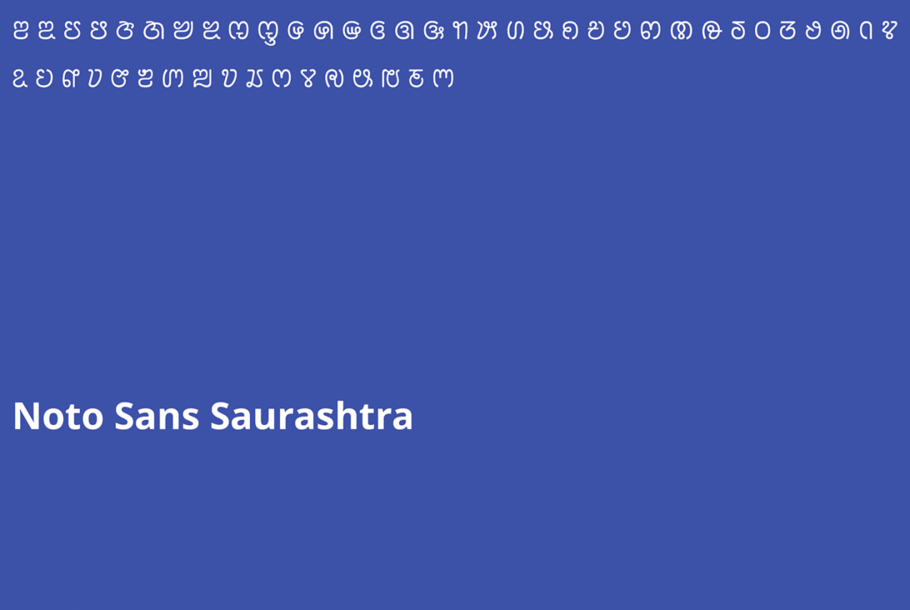
Noto, créée pour Google et ses plus de 800 langages
Une police - cinq ans de production : la police de caractères Noto créée spécialement pour Google couvre plus de 100 systèmes d’écriture, 800 langues et des centaines de milliers de caractères. Fruit d’une collaboration entre Google et Monotype, Noto permet enfin une forme de communication transparente pour des milliards de personnes souhaitant accéder à des contenus numériques du monde entier.
Le brief : « Fini le tofu ! »
Google a donné à Monotype une mission très claire : « Fini le tofu ! ». «Tofu», c’est le surnom que l’on donne aux carrés vides qui s’affichent à la place des caractères lorsqu’un ordinateur ou un site Web ne prend pas en charge la police concernée. Pour répondre à l’exigence de Google, Monotype a dû développer une famille de polices capable de prendre en charge les plus de 800 langues incluses dans la norme du Consortium Unicode.
No More Tofu
Tofu is an old nickname for the boxes that appear when a computer lacks support for a particular writing system or character.
Pour ce travail gigantesque, une nécessité : un design et un développement harmonieux pour une quantité jusqu’alors inégalée de scripts, incluant plusieurs systèmes d’écritures rares qui n’avaient jamais été numérisés auparavant. « Ce fut un projet vraiment extraordinaire et titanesque », déclare Bob Jung, expert en internationalisation chez Google. « En y repensant, je suis moi-même surpris de constater à quel point nous avons été ambitieux. »
« Notre objectif principal pour Noto était de créer des polices pour nos appareils, mais nous accordons aussi un réel intérêt à la préservation des informations », ajoute-t-il. « Qu’il s’agisse des langues les moins utilisées, des langues purement académiques ou des langues mortes, nous pensons qu’il est précieux de les garder quelque part en vie. »
En reposant sur une philosophie de design open source, le projet a mis en liaison des designers et des linguistes du monde entier pour perfectionner la forme de chaque lettre. Autant dire un effort de recherche intense et coordonné, auquel se sont aussi joints de nombreux experts culturels pour étudier les nuances de chaque style, tout en prenant en compte les commentaires directs des communautés utilisant l’écriture. Cinq années passionnantes pour atteindre la version actuelle.
“ Certains caractères n’apparaissent que sur des pierres. Sans la numérisation, ces pierres finiront par se transformer en sable et nous ne pourrons jamais récupérer ces dessins ou cette écriture. ”
La recherche : préservation culturelle
Pour donner une nouvelle identité à l’adlam (un système d’écriture inventé en Afrique en 1989 pour écrire le peul), Monotype a travaillé avec les créateurs de l’écriture originale. Être en lien direct avec les inventeurs de ce système d’écriture a permis aux designers d’intégrer des choix stylistiques et des caractéristiques qui reflètent les intentions initiales des créateurs, et ce fut pour la communauté linguistique peule la première occasion d’utiliser leur écriture sur ordinateur.
Adlam
Adlam was the first time in Monotype’s 100+ year history that the type designers worked directly with the script inventors. This is an early drawing of Adlam characters.
Pour la version arménienne de Noto, des éléments traditionnels et contemporains ont été mélangés, ce qui a permis d’impliquer directement la communauté arménienne dans le processus de conception, tandis que des moines tibétains ont donné leur retour d’expert sur la version tibétaine. Cette écriture, empilée verticalement, a constitué un défi unique. Son élaboration rassemble l’étude du système d’écriture par le designer typographique senior de Monotype Toshi Omagari, aidé de Shojiro Nomura, un érudit bouddhiste, ainsi que l’étude continue du manuscrit par les moines eux-mêmes.
Tibetan
This is a page from the notebook that Toshi Omagari kept while studying the calligraphic traditions of Tibetan.
Noto fut également l’occasion de donner vie à une version numérique du ourdou nastaliq, permettant un meilleur accès aux 100 millions de personnes qui l’utilisent, ainsi que de redynamiser l’ogham (un alphabet datant du IVe siècle et que l’on trouve principalement sur les monuments et les manuscrits). Steve Matteson, directeur de la création typographique chez Monotype, a déterré de nombreuses images de l’écriture médiévale pour créer la version ogham de Noto. « Certains caractères ne se trouvent que sur des pierres. Si nous ne les numérisons pas maintenant, ces pierres finiront par se transformer en sable et nous ne pourrons plus jamais récupérer ces dessins ou cette écriture », explique Xiangye Xiao, chef de produit Noto chez Google.
Le résultat : un langage numérique pour chacun
En plus du rôle culturel joué par son élaboration, Noto est une machine numérique ultra-performante qui donne vie au texte affiché sur les appareils Android et Chrome, et couvre un grand nombre de styles comportant jusqu’à huit graisses. Elle prend en charge les symboles, les emojis et la notation musicale.